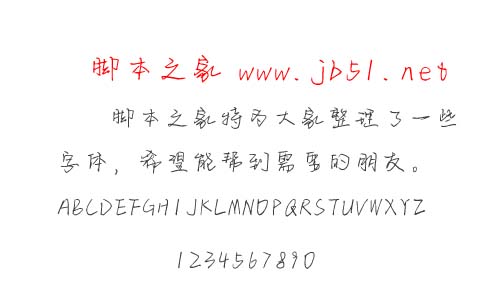
伯樂(lè)俏皮體字體是一款用于飄逸設(shè)計(jì)方面的字體,該字體線條粗細(xì)適中,字形帶有卡通風(fēng)格,結(jié)構(gòu)清晰,風(fēng)格統(tǒng)一,可用于包裝印刷、平面廣告、手稿設(shè)計(jì)、正文標(biāo)題等應(yīng)用,歡迎有喜歡或需要此字體的朋友們前來(lái)下載使用。